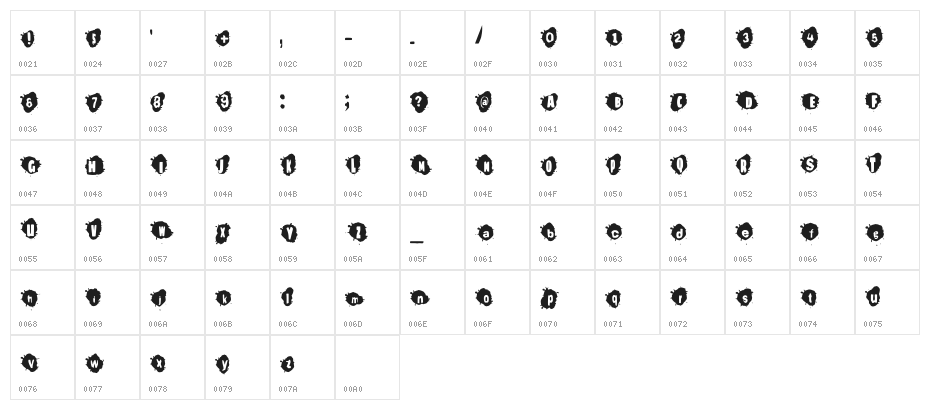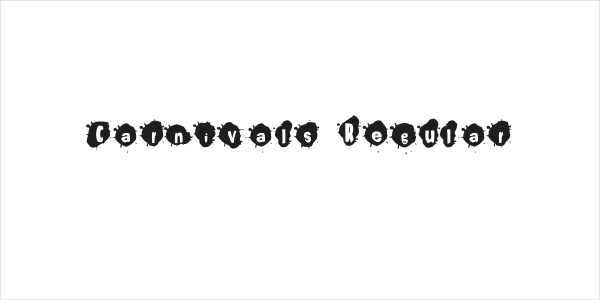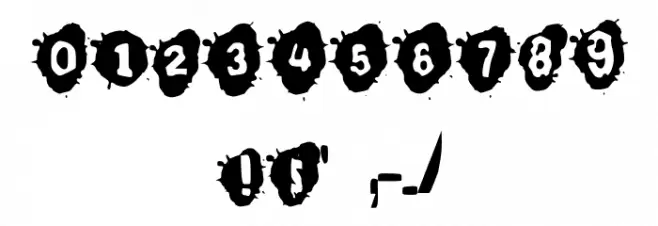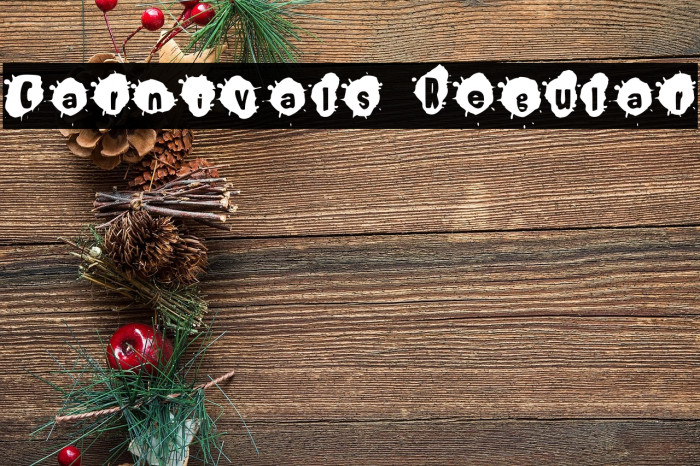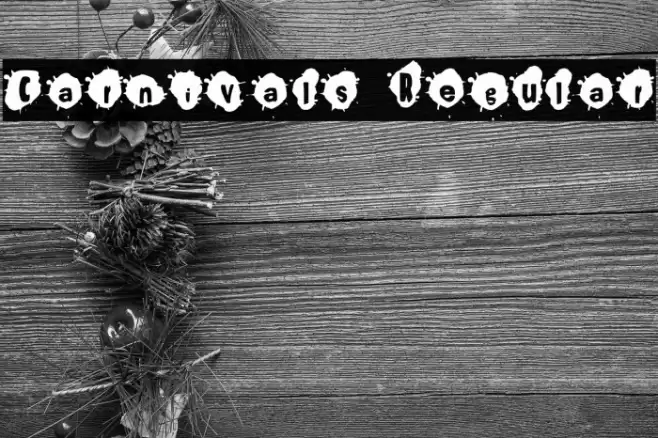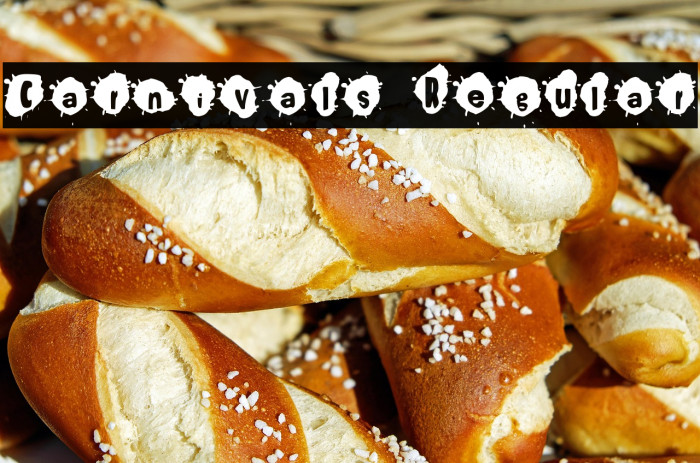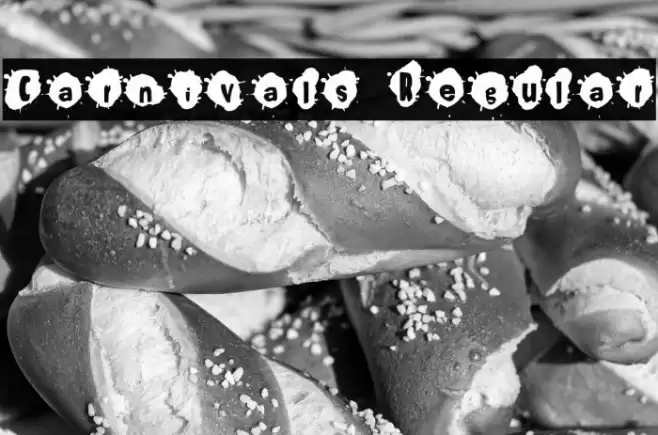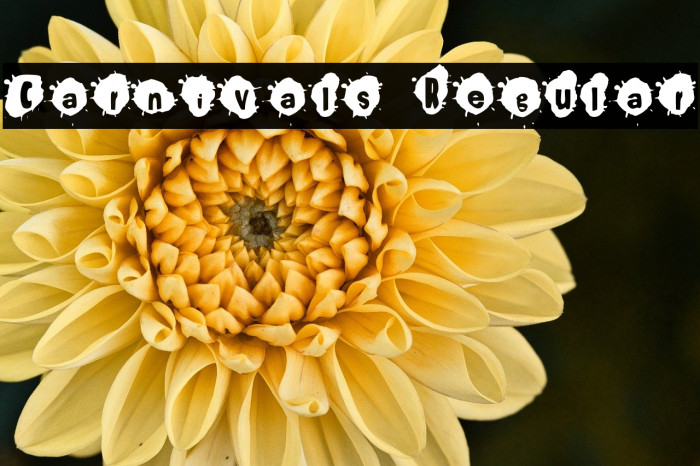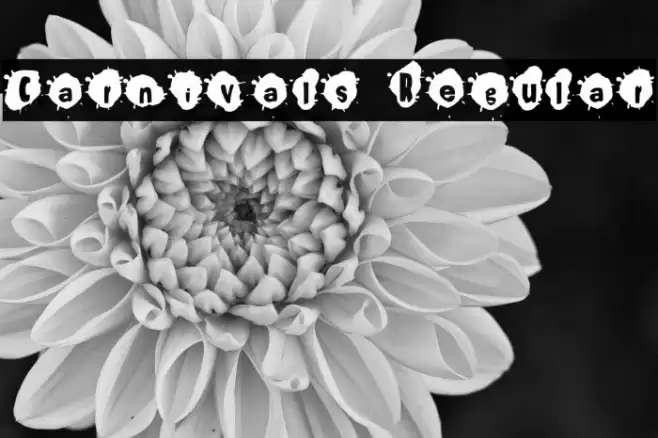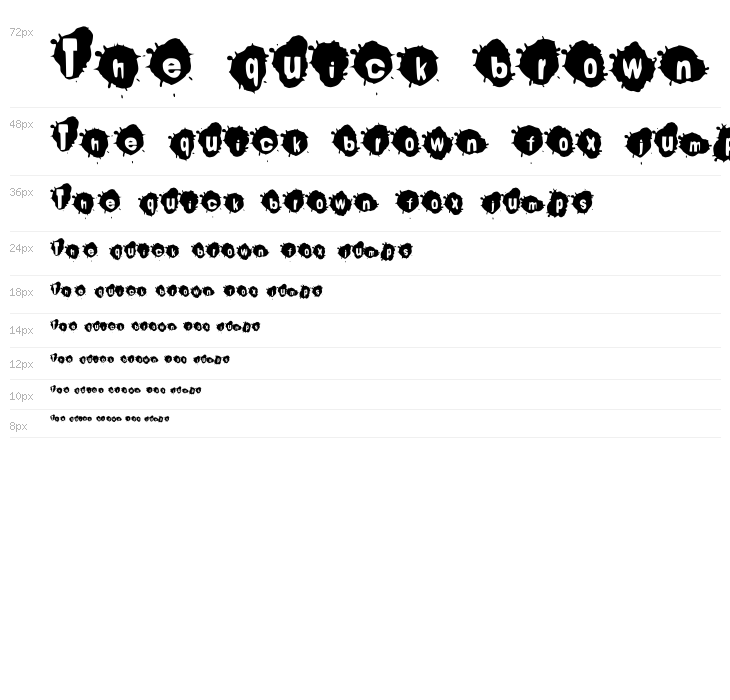
Carnivals Regular Font
| Рекомендуемые проекты | Ideal for creative projects such as event posters, party invitations, children's book covers, or any design requiring a fun and dynamic look. |